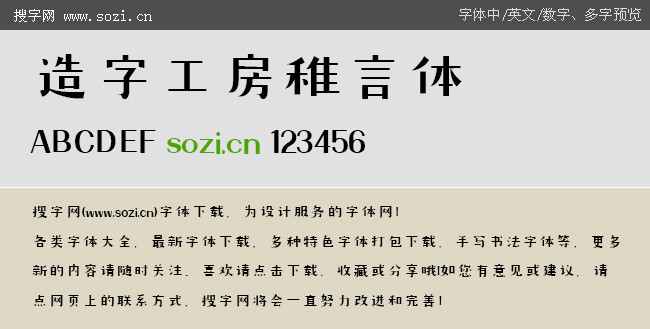
造字工房稚言體
搜字網(wǎng)給大家提供一款造字工房稚言體中文字體下載,其字型設(shè)計(jì)隨性,筆畫舒展有力,結(jié)體寬扁卻不粗臃,左右部件參差錯(cuò)落,卻不失平衡之感,多處創(chuàng)新處理令其節(jié)奏感更強(qiáng),更加靈動充滿張力。適合應(yīng)用于玩具包裝設(shè)計(jì)、兒童用品宣傳設(shè)計(jì)、卡通書籍繪本設(shè)計(jì)、網(wǎng)頁設(shè)計(jì)等應(yīng)用。(本字體為個(gè)人非商用版,如需要商用請聯(lián)系官方購買版權(quán))